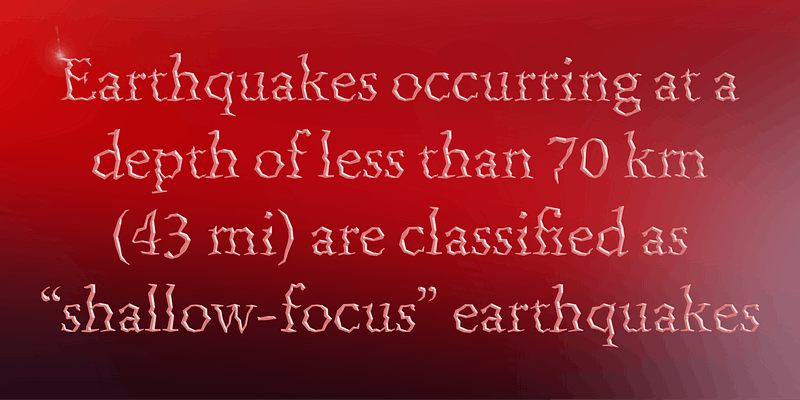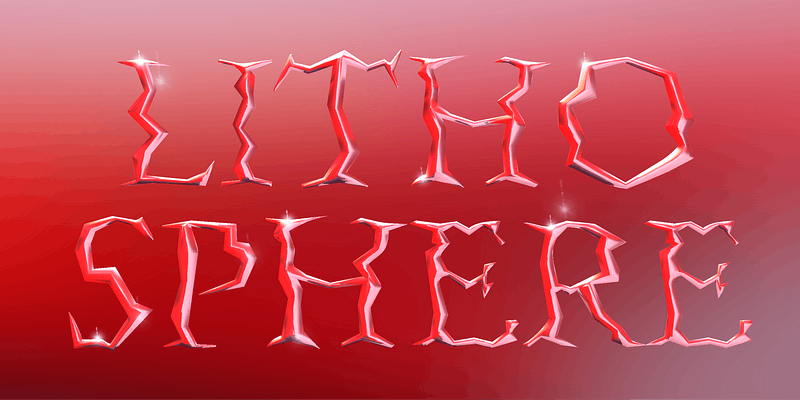
À la suite du tremblement de terre de San Francisco de 1989, Fryda Berd d’Adobe a conçu Quake pour montrer que quelque chose de constructif peut naître d’un événement destructeur.